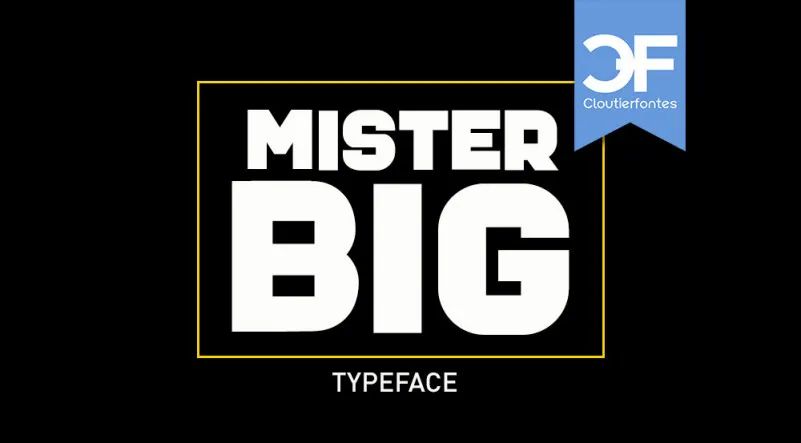
Mister Big Font – Fonte Grátis
Mister Big Font
A fonte Mister Big Font é uma opção ideal para quem procura um charme único para projetos que exigem destaque. Esta display font contém caracteres especiais perfeitos para as necessidades de criações de marca, logotipos, designs de casamentos, posts de mídia social, anúncios, embalagens de produtos, desenho de produtos, etiquetas, fotografias e até mesmo marcas nas fotos. Suas características curvilíneas e extensões criam um visual atraente que é perfeito para qualquer projeto que necessite de uma mão escrita única e distintiva. Foi desenvolvida por 99designs, uma plataforma conhecida por oferecer fontes de qualidade. Idealmente usada em projetos digitais ou impressos que buscam destacar-se, a Mister Big Font é uma escolha inteligente para qualquer criador de conteúdo gráfico em busca de um visual único e impressionante. Suas linhas fortes e expressivas combinam perfeitamente com as necessidades de criação que exigem destaque e originalidade.